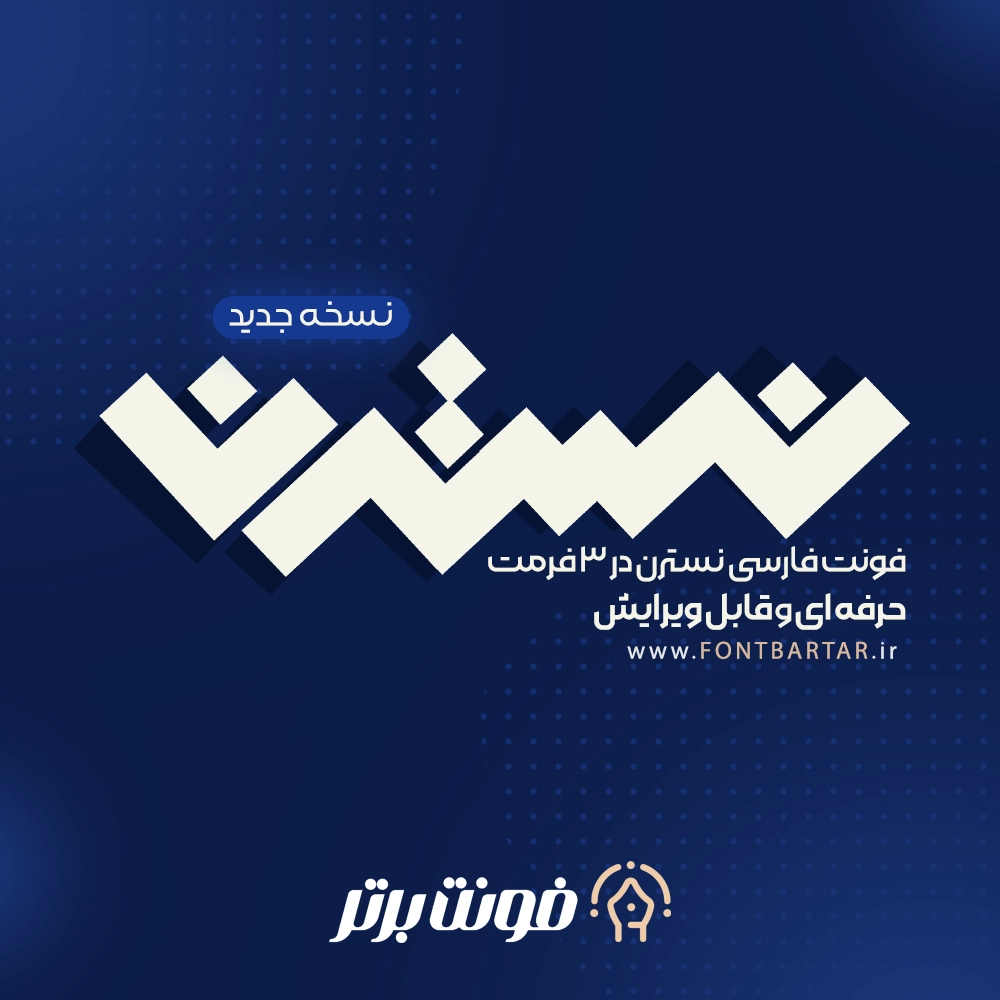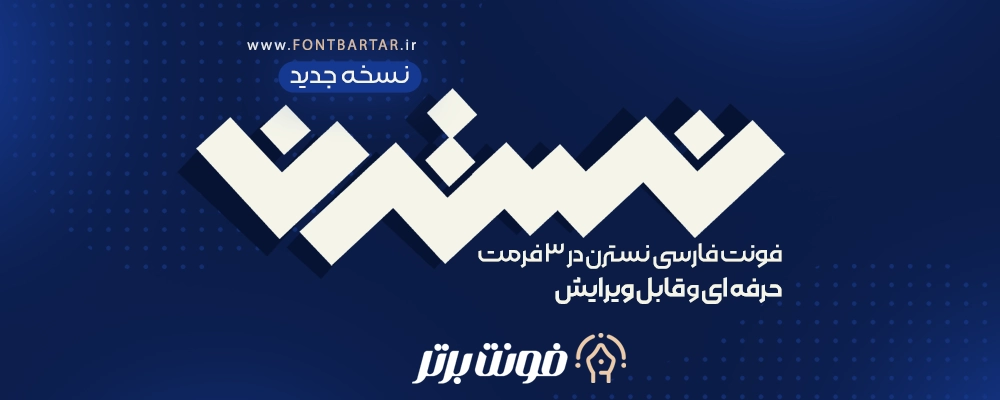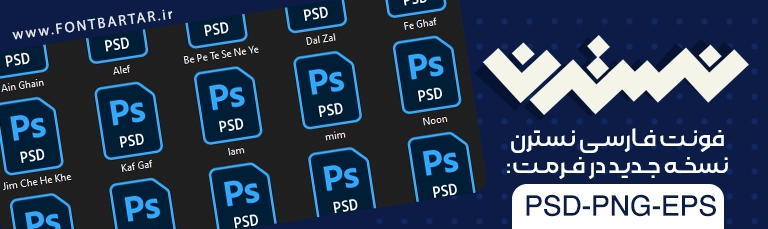
فونت لایه باز نسترن
فونت فارسی نسترن
Nastaran Font
فونت لایه باز فارسی یکی دیگر از فونت های طراحی لوگوتایپ و تایپوگرافی می باشد، فونت فارسی نسترن با طراحی حرفه ای و انعطاف پذیر می باشد و این امکان را فراهم می آورد که به راحتی بتوانید حروف را در کنار هم قرار دهید، با خرید فونت نسترن می توانید بدون هیچگونه دانشی لوگو تایپ طراحی کرده و تایپوگرافی های زیبایی انجام دهید و از آن کسب درآمد کنید.
فونت نسترن بر خلاف سایر فونت ها به صورت لایه باز بوده (psd) و امکان تایپ مستقیم در نرم افزار ها را ندارد همچنین شامل تمامی حروف از الف تا ی می شود این فونت به چینش های مختلف می تواند در کمترین زمان این امکان را به طراح بدهد که یک لوگو تایپ حرفه ای برای کسب و کار های مختلف طراحی کند ویژگی های این فونت حرفه ای را باهم مرور کنیم.
📌مزایای استفاده از فونت زیبا نسترن:
• لوگوتایپ فارسی تمامی حروف به صورت لایه باز
• فونت لایه باز ویرایش آسان حروف
• طراحی لوگوتایپ
• طراحی لوگو به صورت آسان و بدون هیچگونه آموزش
• فونت زیبا نسترن شامل تمامی حروف از الف تا ی در تمامی حالت ها
• دانلود فونت لوگو فارسی نسترن مناسب عناوین و تیتر ها
• فونت مناسب کاور اینستاگرام و یوتیوب
• فونت لوگو بهترین گزینه برای تایپوگرافی پوستر ها
• گزینه مناسب برای طراحی لوگوتایپ سنگین